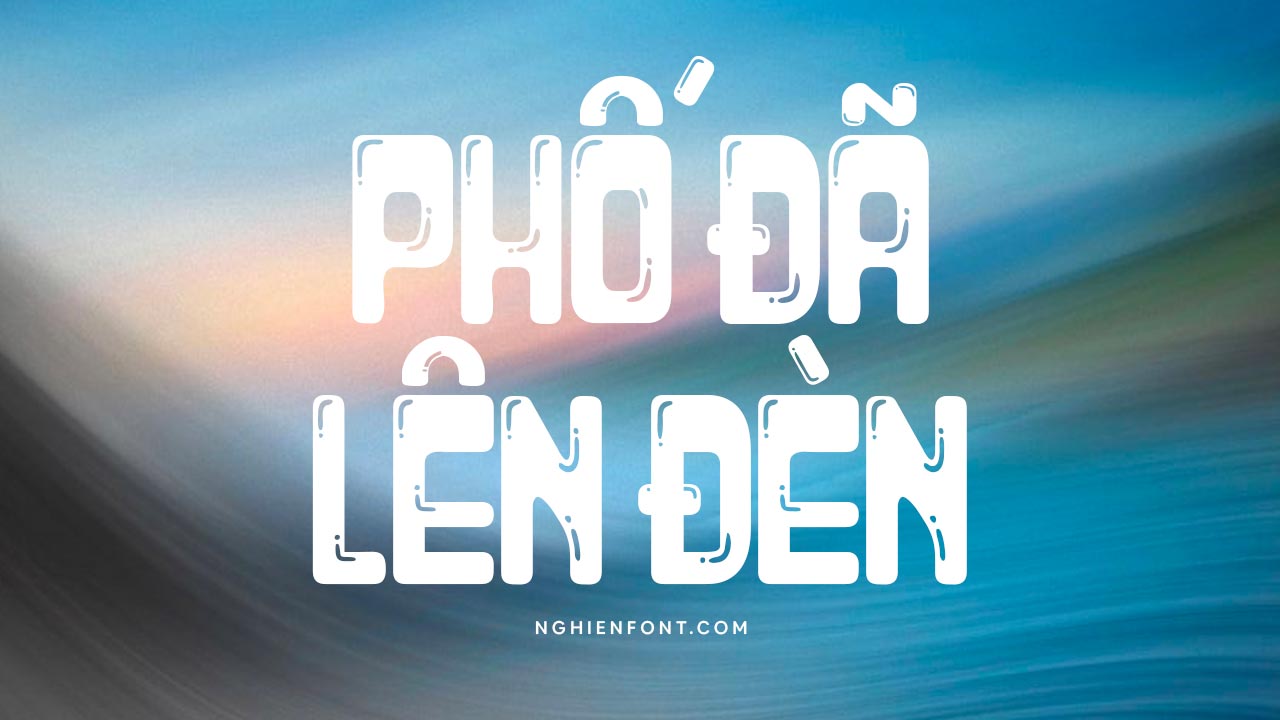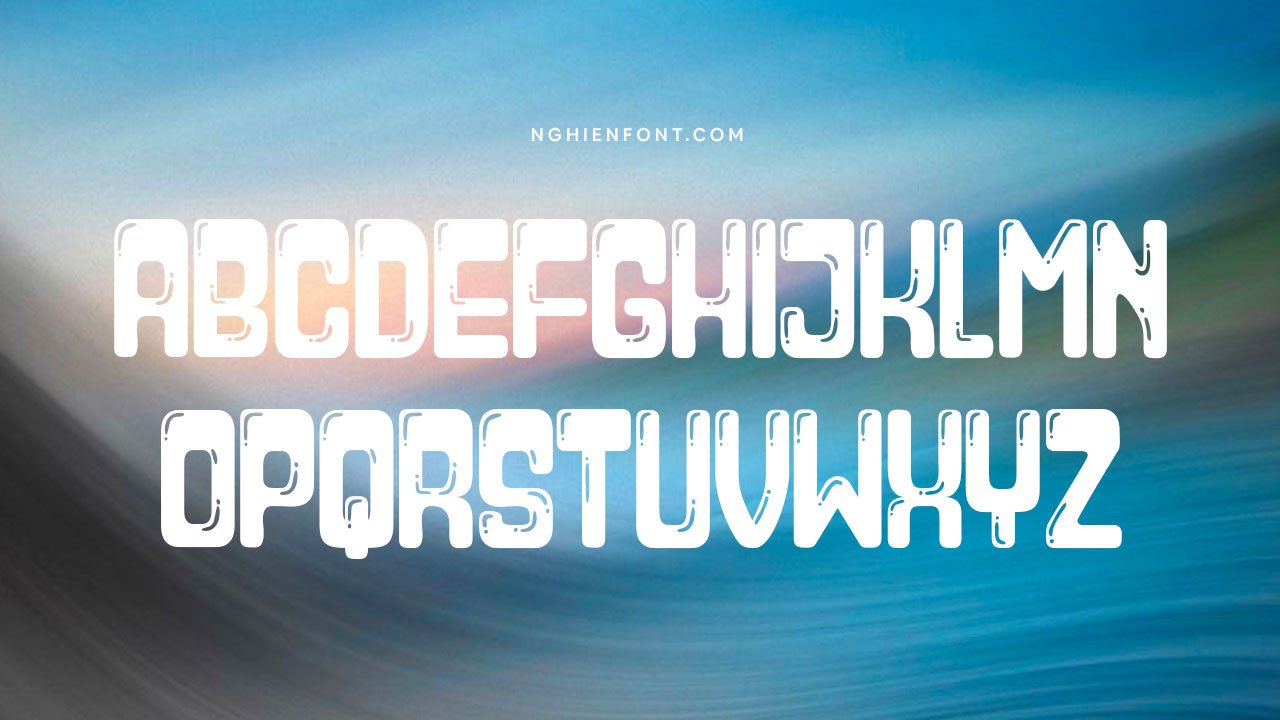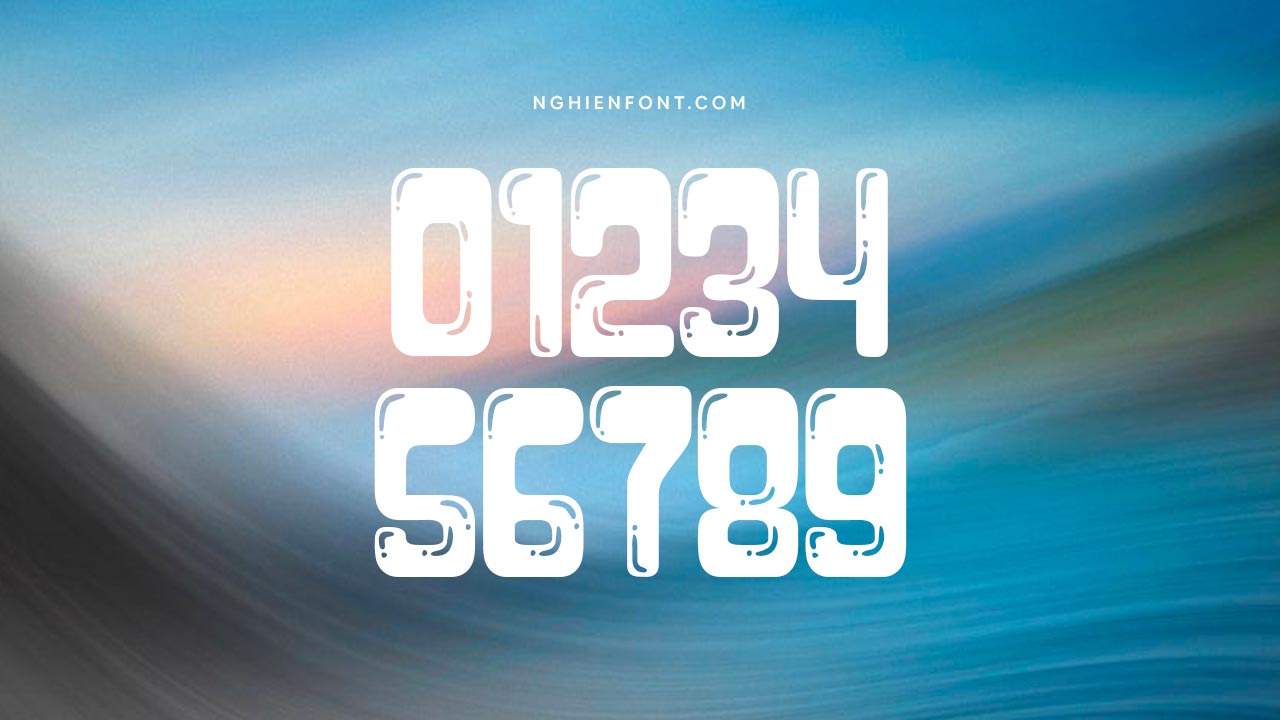
LNTH Paraglide là một kiểu phông chữ bong bóng với các nét chữ dày đậm, tất cả các chữ cái đều in hoa, mang đến vẻ ngoài ấn tượng, đúng như tên gọi của nó Paraglide (dù lượn).
Font chữ này sẽ tuyệt vời khi sử dụng cho các thiết kế như áp phích, tờ rơi, thiệp mời, poster, trang trí hoặc bất kỳ thiết nào khác cần một kiểu chữ hiển thị lạ mắt và độc đáo.